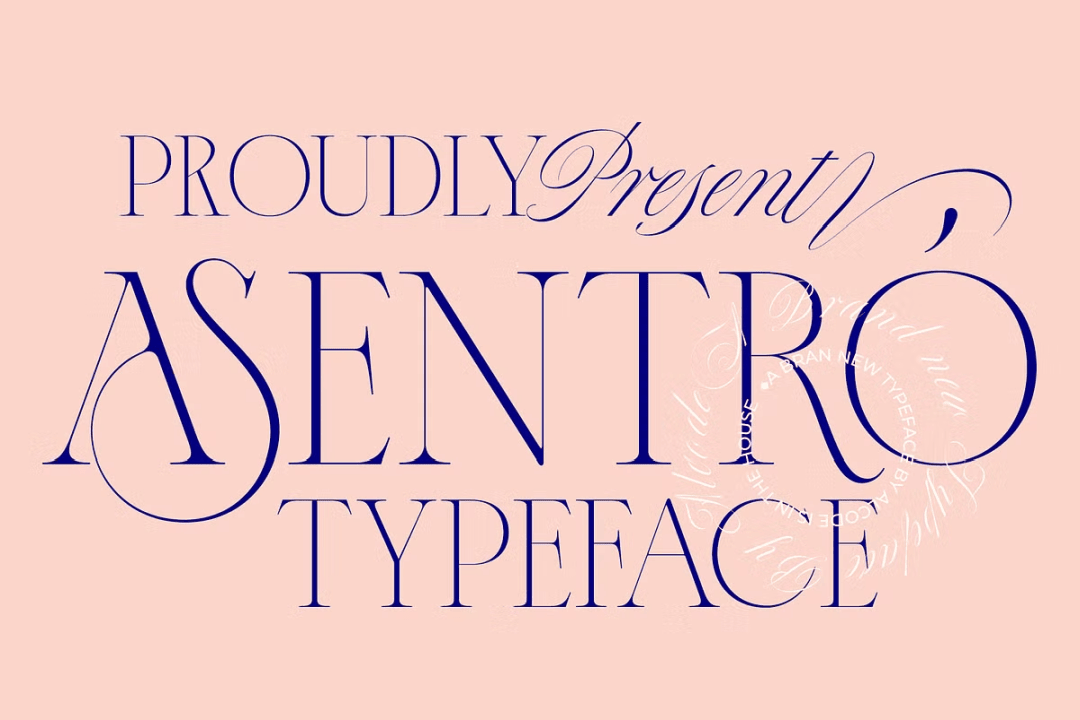
Asentro
繊細でクラッシーなモダンローマンディスプレイ。よくあるリガチャーとオルタネートが豊富な書体で、大変美しくエレガントな雰囲気を持っている。この手としては珍しくファミリー展開をしており、Thin から Black まで9ウェイトもある。また小文字もちゃんとあって使い勝手がいいだろう。Creative Market は去年辺りからファミリーでもバラで購入できるようになっており、必要なウェイトだけ買うこともできる。が、この書体は2つ分で全ファミリーパックの価格を超えてしまうので、パックで買った方がお得だろう。画像内のスクリプトは同じ作者による Bustra